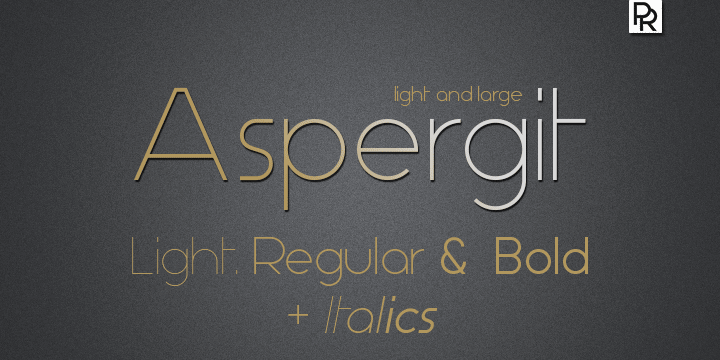
Bem-vindo ao download da Aspergit Font Family! Eu soube que você estava procurando uma fonte linda para seu próximo projeto e aqui está algo especial. A Aspergit é um tipo gótico livre de traços perfeitamente adaptado para o uso pessoal ou comercial, e isso é possível graças ao nosso compromisso com a liberdade criativa. Além disso, estou em constante expansão, permitindo que você personalize ainda mais seu design. Quer entender melhor quem somos? Eu soube há um tempo que estava na web me seguindo no Facebook: https://www.facebook.com/Skomii.PauloR. Foi assim que fiquei por dentro de todas as minhas criações e novidades. Se você também está curioso sobre o meu trabalho, acesse esse link para explorar mais! A Aspergit tem um estilo elegante e moderno, perfeito para qualquer design, seja em cartazes ou aplicativos móveis. E com seu designer, Hamilton, fazendo o possível para manter essa beleza clássica ao mesmo tempo que oferece uma aparência atualizada e funcional. Em suma, está aqui na sua tela – um novo recurso de gráficos para você!